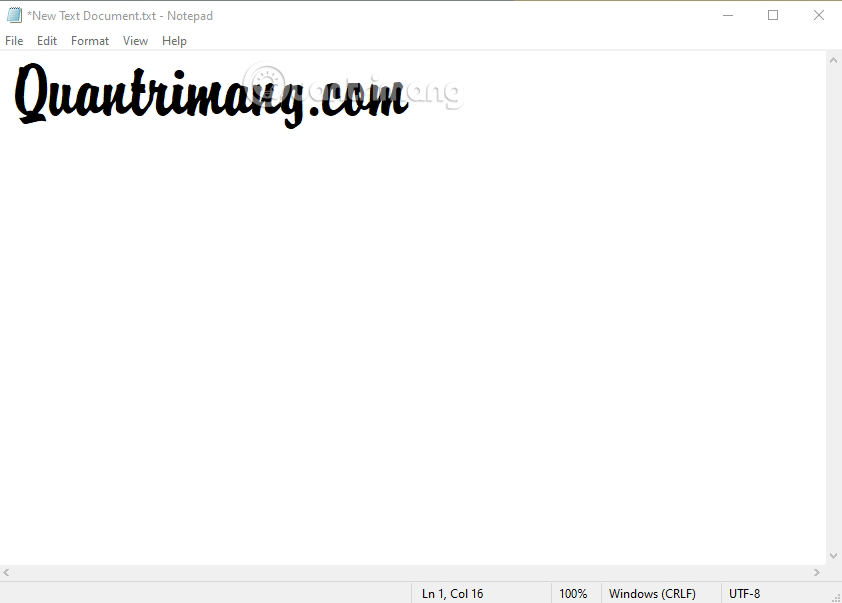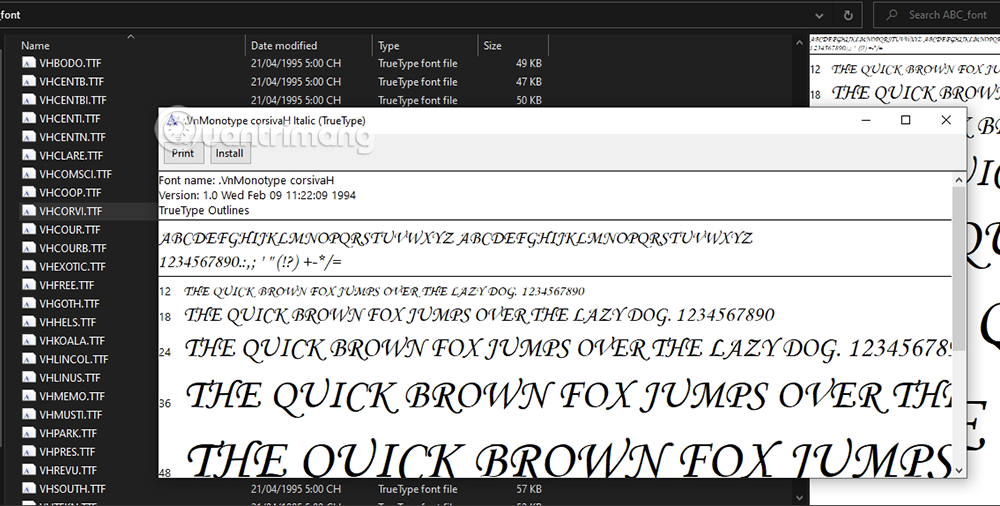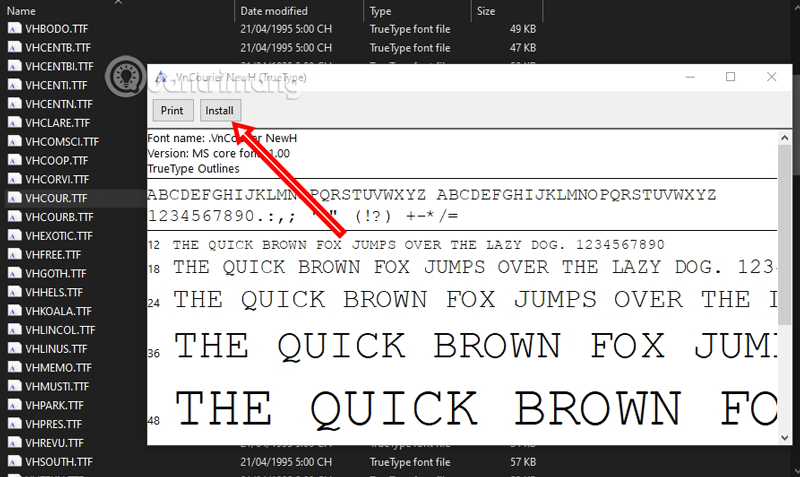
Font Full
Bộ Font Full này sẽ mang đến cho người dùng những font chữ tiếng Việt phổ biến nhất hiện tại để bạn thoải mái thay đổi và lựa chọn các font chữ phù hợp để soạn thảo văn bản, thiết kế, trò chuyện hoặc sử dụng trong Photoshop.
Dù có nhiều công cụ chỉnh sửa online như Canva hỗ trợ người dùng các font chữ bay bổng, hiện đại. Nhưng nếu muốn sử dụng cho các công cụ soạn thảo văn bản như Microsoft Word, Excel hay PowerPoint thì việc cài đặt các font chữ này sẽ hợp lý hơn.
Font Full sẽ chứa nhiều font chữ khác nhau từ cổ điển cho đến hiện đại, bạn có thể thay đổi tùy vào dự án mà bạn đang hoàn thiện. Trong mỗi bộ font chữ đều có những đặc trưng riêng, nhằm thỏa mãn nhu cầu sáng tạo của các nhà thiết kế.
Đa phần những phần mềm, ứng dụng đều sẽ có những font chữ phổ biến và sẽ tích hợp thêm những font chữ được cài đặt trên máy. Bộ Font Full này sẽ đem đến cho bạn nhiều font chữ và chúng sẽ phù hợp với nhiều phần mềm.
Bộ Font Full hiện tại đã được bổ sung thêm các Font chữ viết tay và Font chữ Thư Pháp. Bạn có thể thoải mái lựa chọn Font chữ yêu thích. Thậm chí bạn có thể trở thành một nhà thư pháp thực sự với những mẫu chữ thư pháp hợp cảnh.
Kèm theo những font chữ hiện đại, chữ tiểu học phù hợp để giảng dạy và soạn giáo án cho các giáo viên. Bạn có thể tạo ra một văn bản với font chữ Tiểu Học để làm mẫu cho các em học sinh luyện tập theo.
Font chữ đa dạng sẽ giúp cho người dùng thoải mái sử dụng trên nhiều phần mềm và thỏa mãn sức sáng tạo của người dùng. Đáp ứng đầy đủ những nhu cầu phức tạp của bạn, đặc biệt là khi bạn sử dụng nhiều ngôn ngữ đa dạng trên các phần mềm khác nhau.